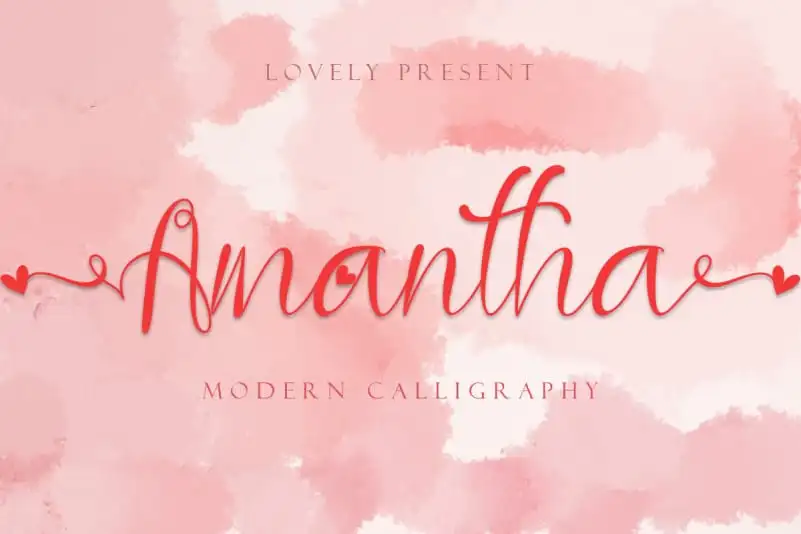
Amantha Calligraphy Font – Download Grátis
Amantha Calligraphy Font é uma escolha única para quem busca um toque especial em suas criações digitais. Com seu design único e swashes e alternativas extremamente bonitas, esta fonte se destaca no mercado de calligrafia digital. As alternativas da Amantha são facilmente utilizáveis e podem ser usadas em diversas situações, desde momentos românticos até celebrações de aniversário e casamentos, passando por publicidade, citações, postagens na rede social, convites, logotipos e banners. Suas linhas leves e detalhes únicos tornam Amantha Calligraphy Font uma escolha perfeita para quem busca um toque a mais em seus projetos digitais, seja para usar em sites, materiais impressos ou para personalizar mensagens pessoais. Engajante, versátil e fácil de usar, é a fonte ideal que enriquece qualquer projeto, seja ele formal ou informal.